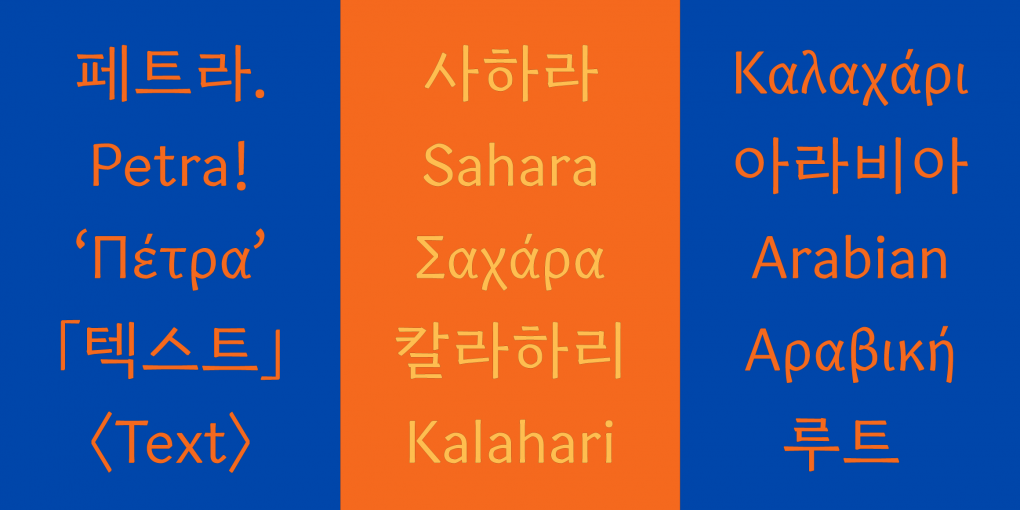
사막과 모래바람 그리고 「SD 페트라」
바위라는 뜻의 페트라 Πέτρα
「SD 페트라」는 기획 초반부터 돌에 새겨진 서사시를 상상하며 작업을 이어왔습니다. 때문에 주로 그리스 서사시를 시안 문구로 삼아 조판 테스트를 하곤 했습니다. ‘페트라Petra, Πέτρα’ 라는 이름 또한 그리스어에서 유래한 이름으로 ‘바위’란 뜻을 가지고 있기도 하고요. 이로 인해 자연스럽게 그릭 문자 세트를 개발해야겠다는 생각이 들었습니다.
그릭 문자는 라틴과 키릴 문자에 영향을 준, 역사와 근본이 깊은 문자인데요, 사실 그릭 문자는 과학과 수학 분야에서 사용되고 있기 때문에 이미 생김새와 이름이 익숙하신 분들이 많을 거예요. (‘알파α’와 ‘파이π’같은 문자들처럼요!) 하지만 디자인한다는 것은 완전히 다른 얘기였죠. 라틴과는 다른 그릭만의 형태적 고유성 때문에 쉽게 접근하기 어려운 부분이 많았기 때문에, 타입 디자이너들과 그릭 스터디를 진행해 그릭 문자를 공부해 본 후 제작하기로 했습니다.
페트라의 형태
「SD 페트라」에는 사람이 쓴듯한 자연스러움을 반영하고 싶었어요. 때문에 자소의 형태에 쓰기 방식이 느껴질 수 있도록 여러 테스트를 거쳤습니다. 먼저 삐침 계열인 ‘ㅅ, ㅈ, ㅊ’를 보면 갈래로 갈라져 내려가는 부분에 단차를 주어 쓰기 방향이 드러날 수 있도록 하였습니다. 세로모임 민글자의 중성 ‘ㅠ’ 또한 삐침 계열과 비슷한 맥락으로 제작했죠.
폰트의 또 다른 특징적인 디테일은 바로 점의 모양입니다. Display는 Text에 비해 더 날카롭고 각진 점이 어울린다고 판단해 형태 자체를 다르게 디자인했어요. 점의 모양에 따른 연계된 글립 모두 동일하게 적용됩니다.
판타지나 SF 장르물의 타이틀과 본문에 어울리는 폰트, 「SD 페트라」!